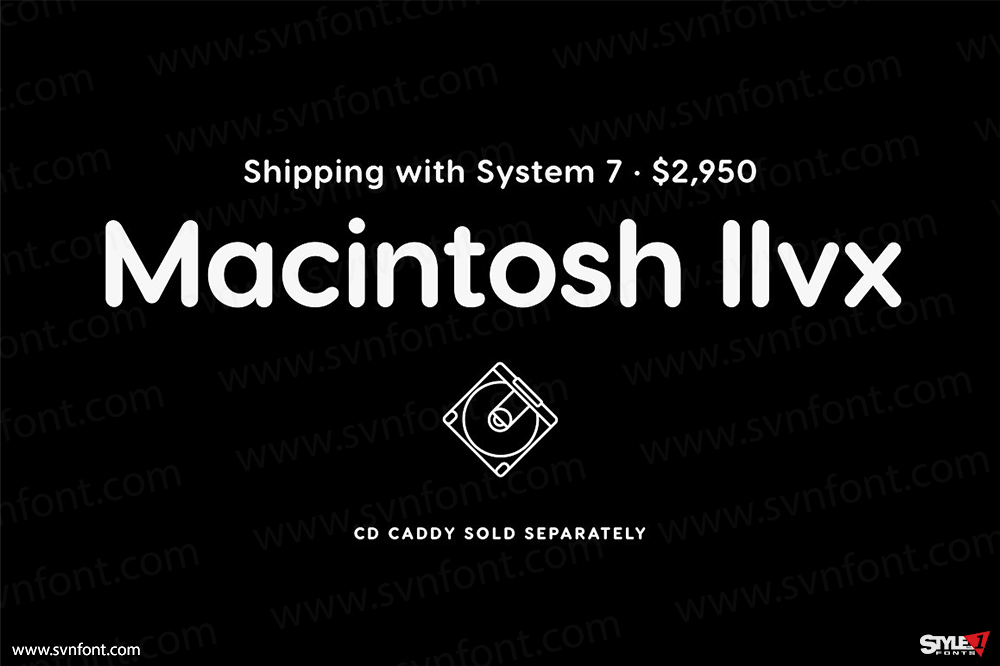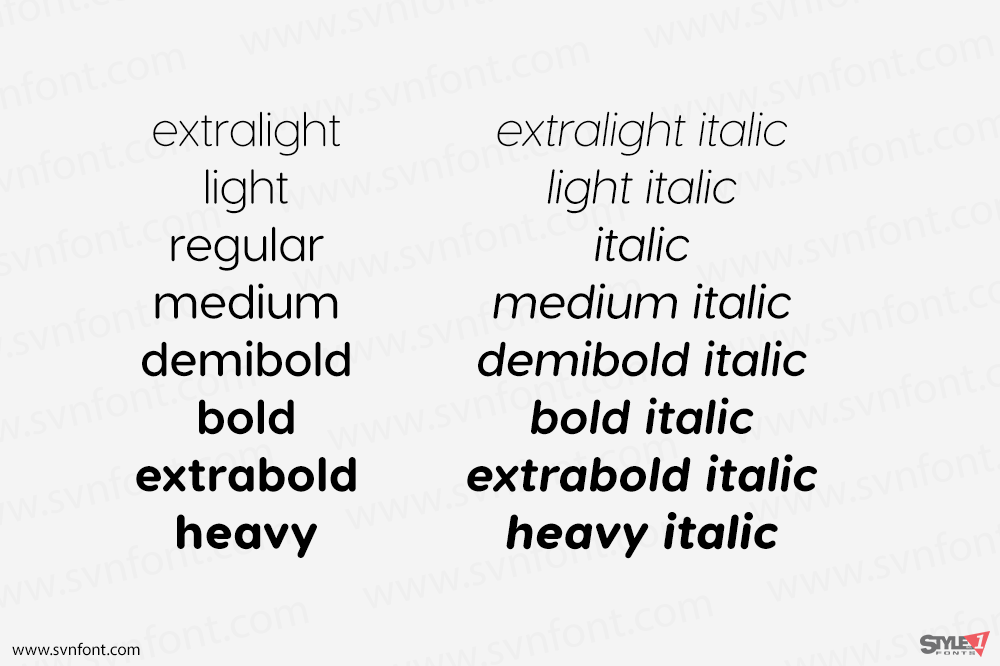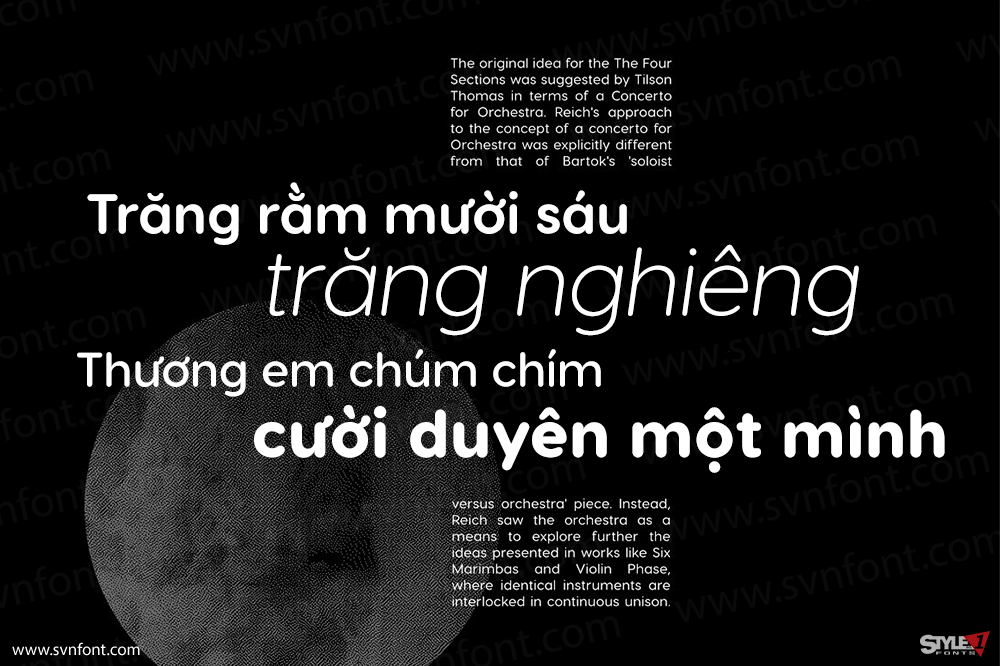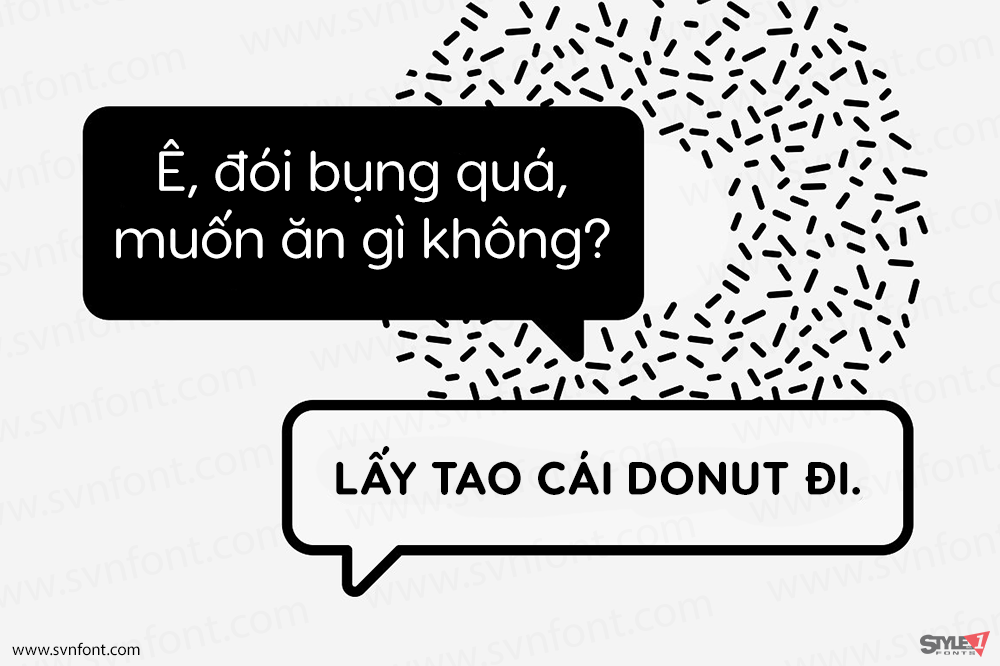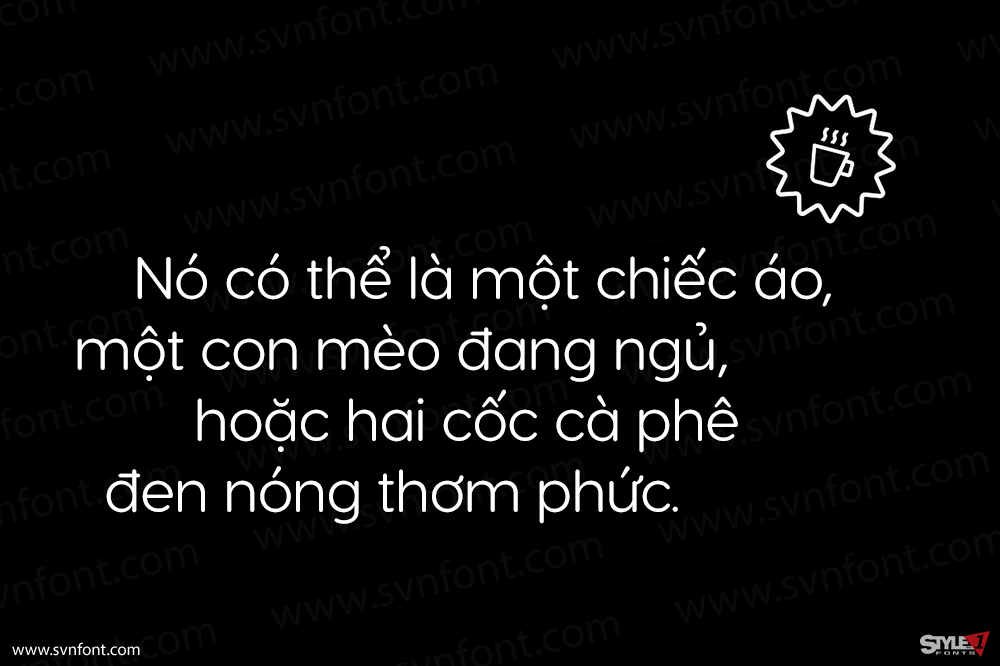
Visby Round CF lấy những hình thái cuốn hút của “người anh em” Visby và làm mềm chúng đi, tạo ra một vẻ ngoài thân thiện, dễ tiếp cận. Hoàn hảo cho bất cứ nơi nào bạn cần một chút sự tốt lành của font sans-serif mượt mà. Bao gồm bộ chữ Latin và Cyrillic. Visby Round CF kết hợp tốt với các kiểu chữ sắc nét, tương phản, đặc biệt là các font serif thân thiện với văn bản như Artifex CF và Addington CF.